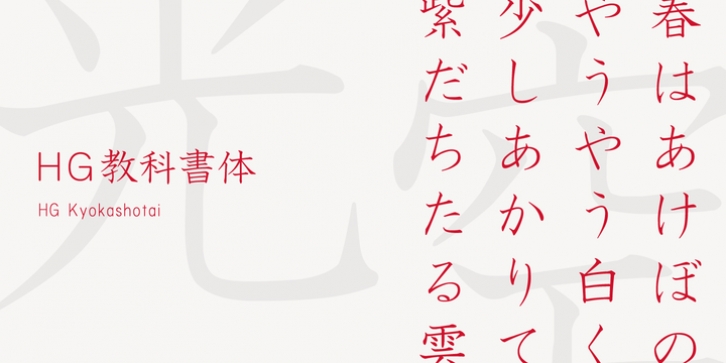
HG教科書体は、日本活字工業の「日活教科書体」を字母とする教科書体で、児童の教科書などの使用が想定される書体です。筆で書いた文字をもとにしていますが、太さはやや細めです。伸びやかで、格調高いデザインの書体で、フォーマルな場面に合います。手書きの要素が強くコントラストも高めなので、小さいサイズでの長文に使用するよりは、それなりのサイズで、かつ、あまり長めでない文章に使用するほうがいいでしょう。